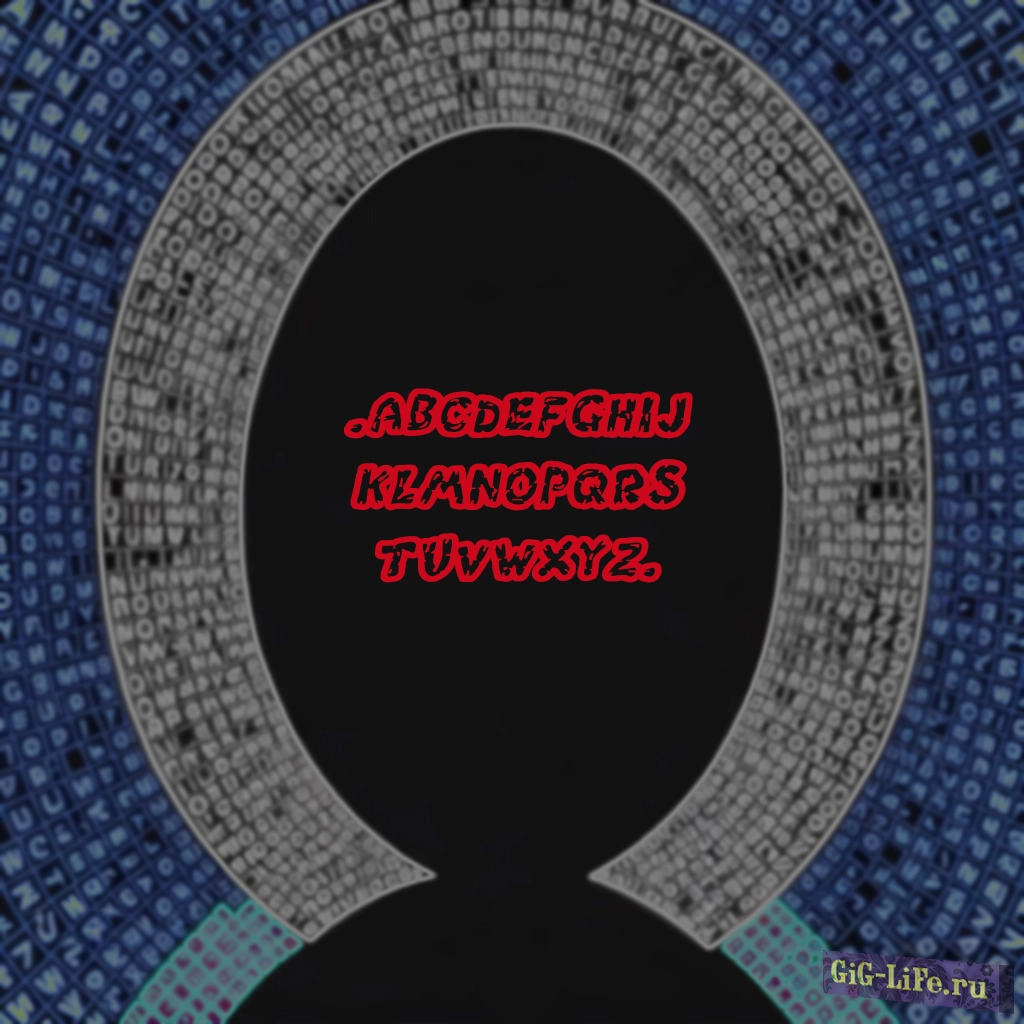
Шрифт — Turtles
Шрифт Turtles — это воплощение стиля и энергии, вдохновлённое знаменитым мультфильмом “Черепашки Ниндзя”. Его буквы, словно созданные для героев-мутантов, обладают выразительными и динамичными линиями, которые сразу же вызывают ассоциации с приключениями и боевыми искусствами.
Каждая буква в этом шрифте тщательно проработана, чтобы создать ощущение силы и уверенности. Шрифт Turtles идеально подходит для оформления комиксов, плакатов, обложек книг и других элементов дизайна, связанных с Черепашками Ниндзя и их захватывающими приключениями. Его выразительные формы и динамичные линии делают любой проект ярким и запоминающимся.
Шрифт Turtles — это не просто набор букв, это символ мужества и дружбы, который вдохновляет и восхищает поклонников Черепашек Ниндзя всех возрастов.